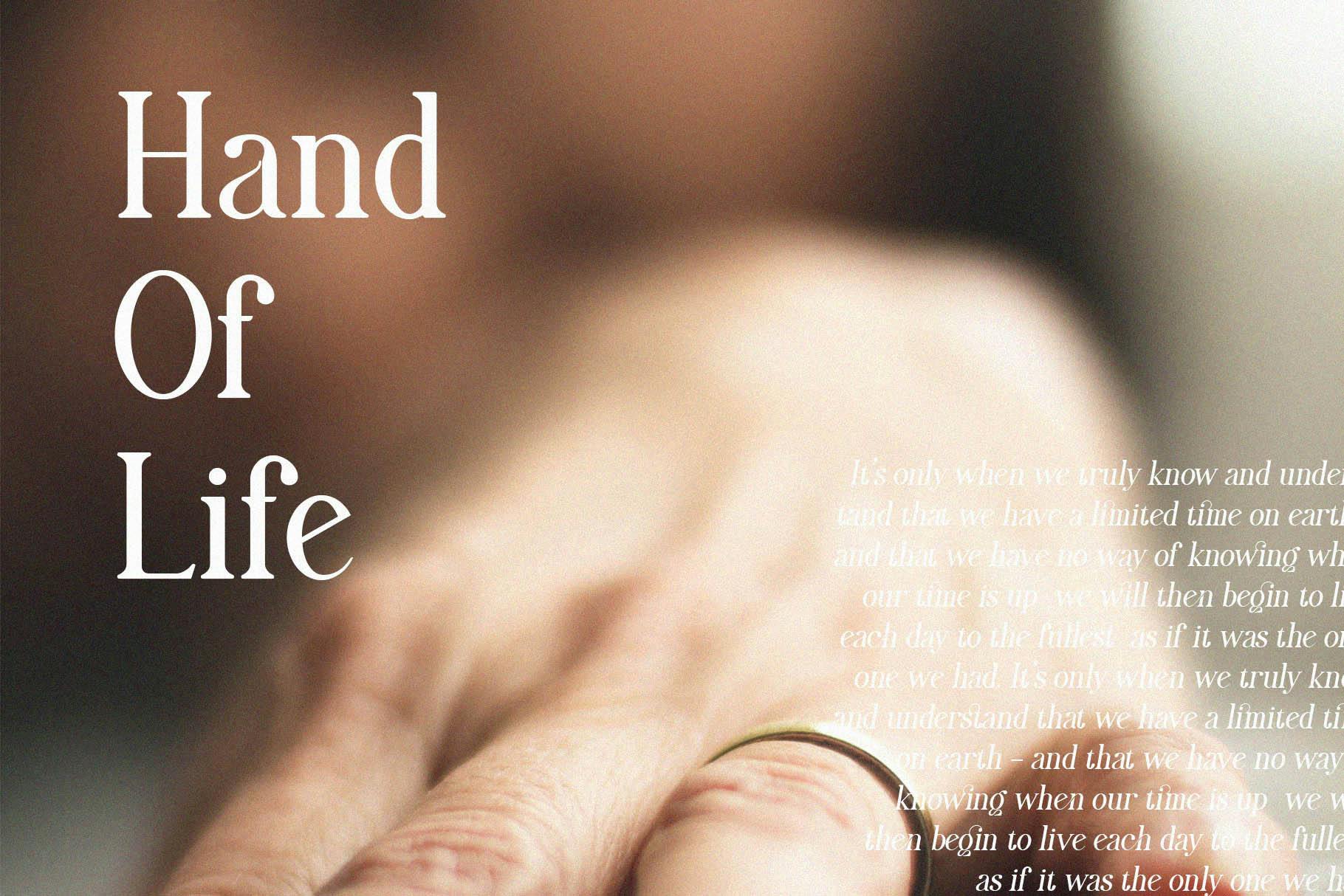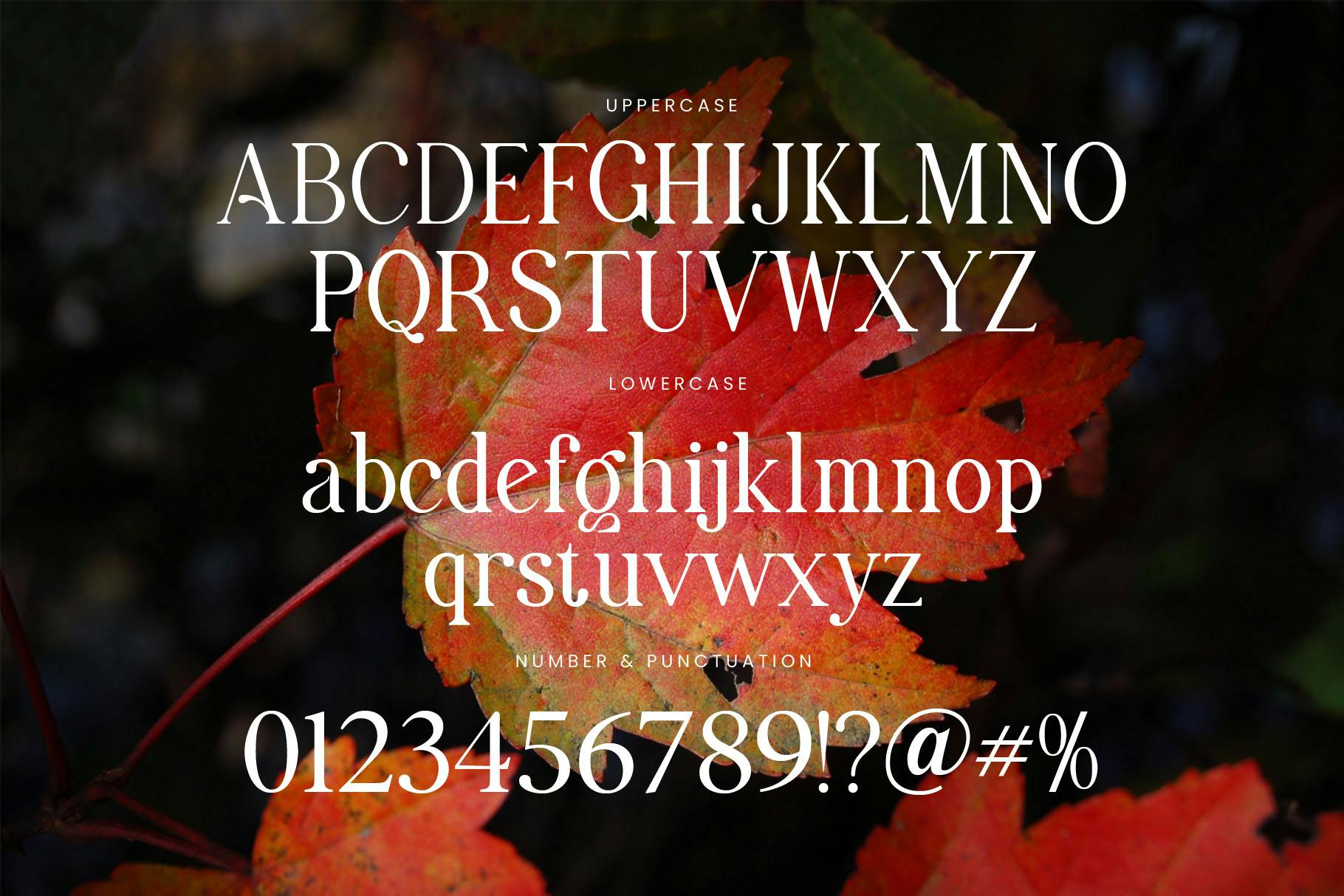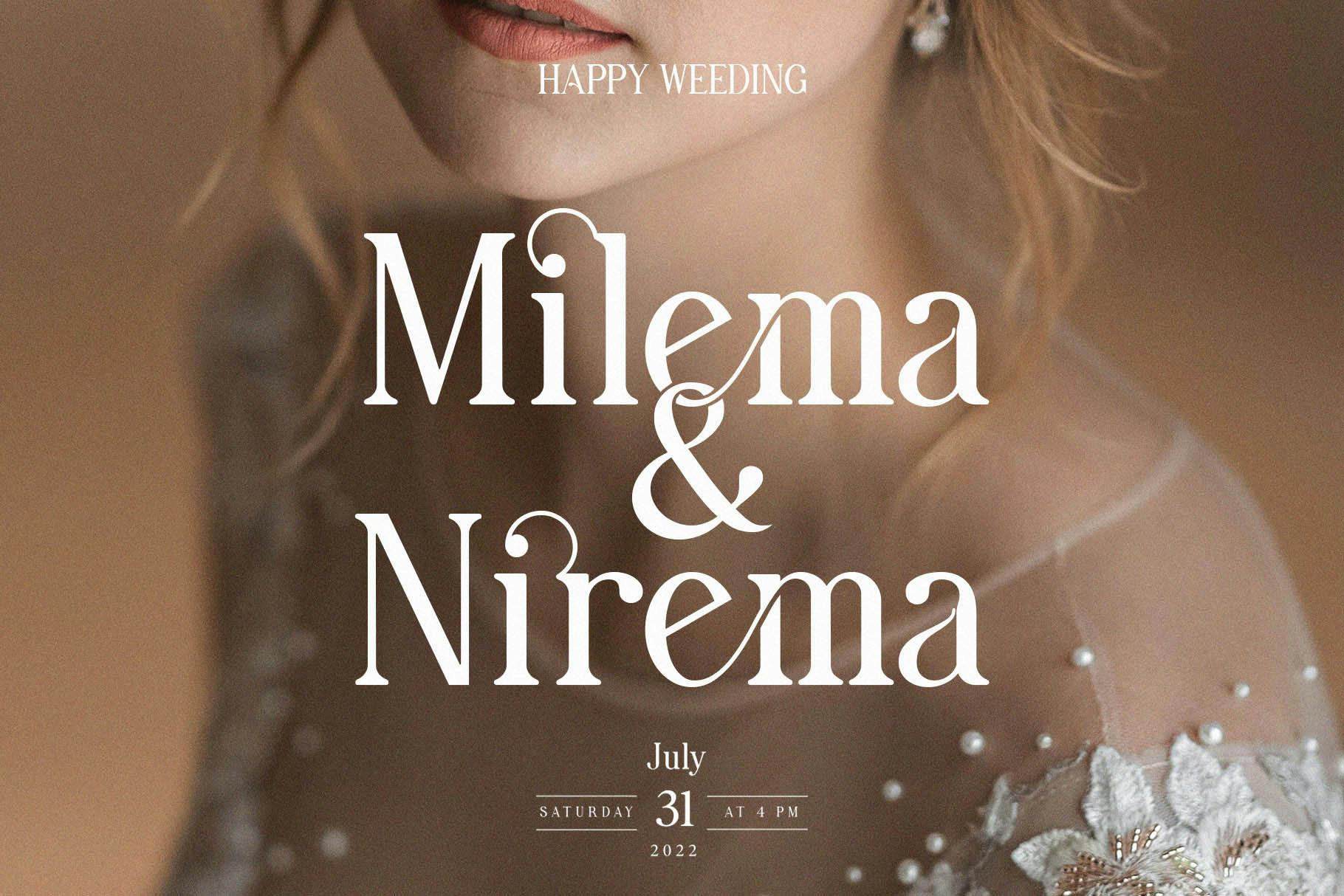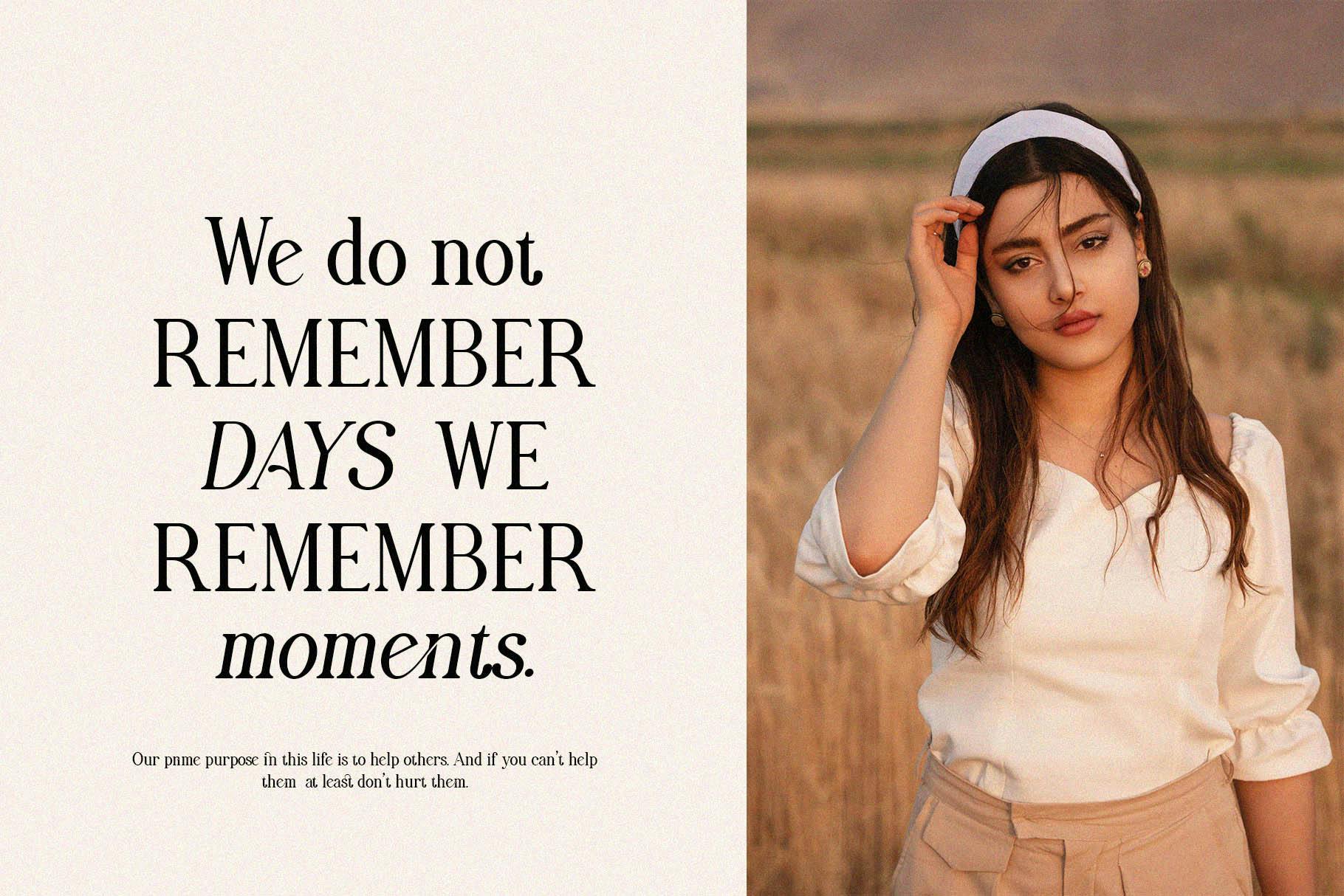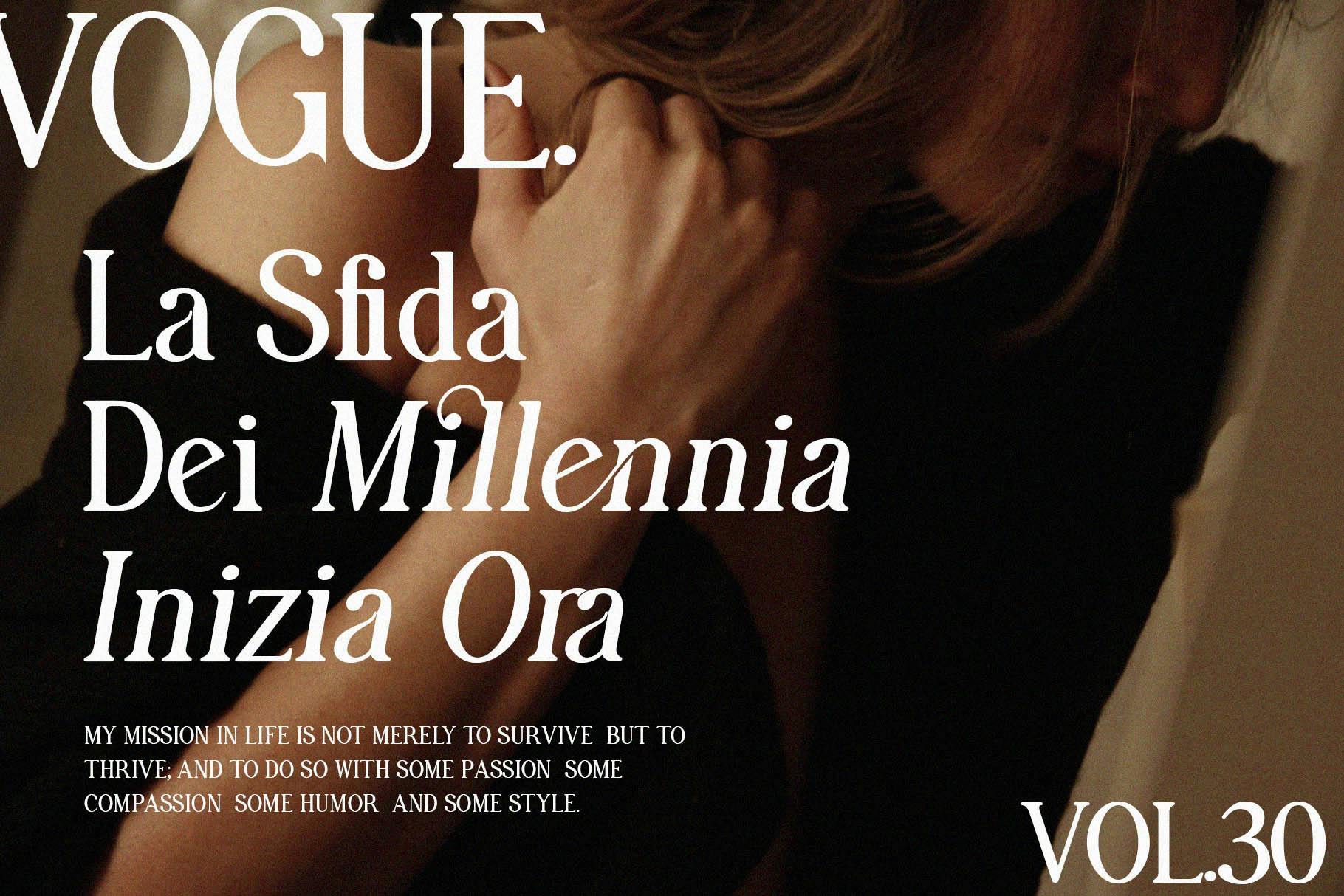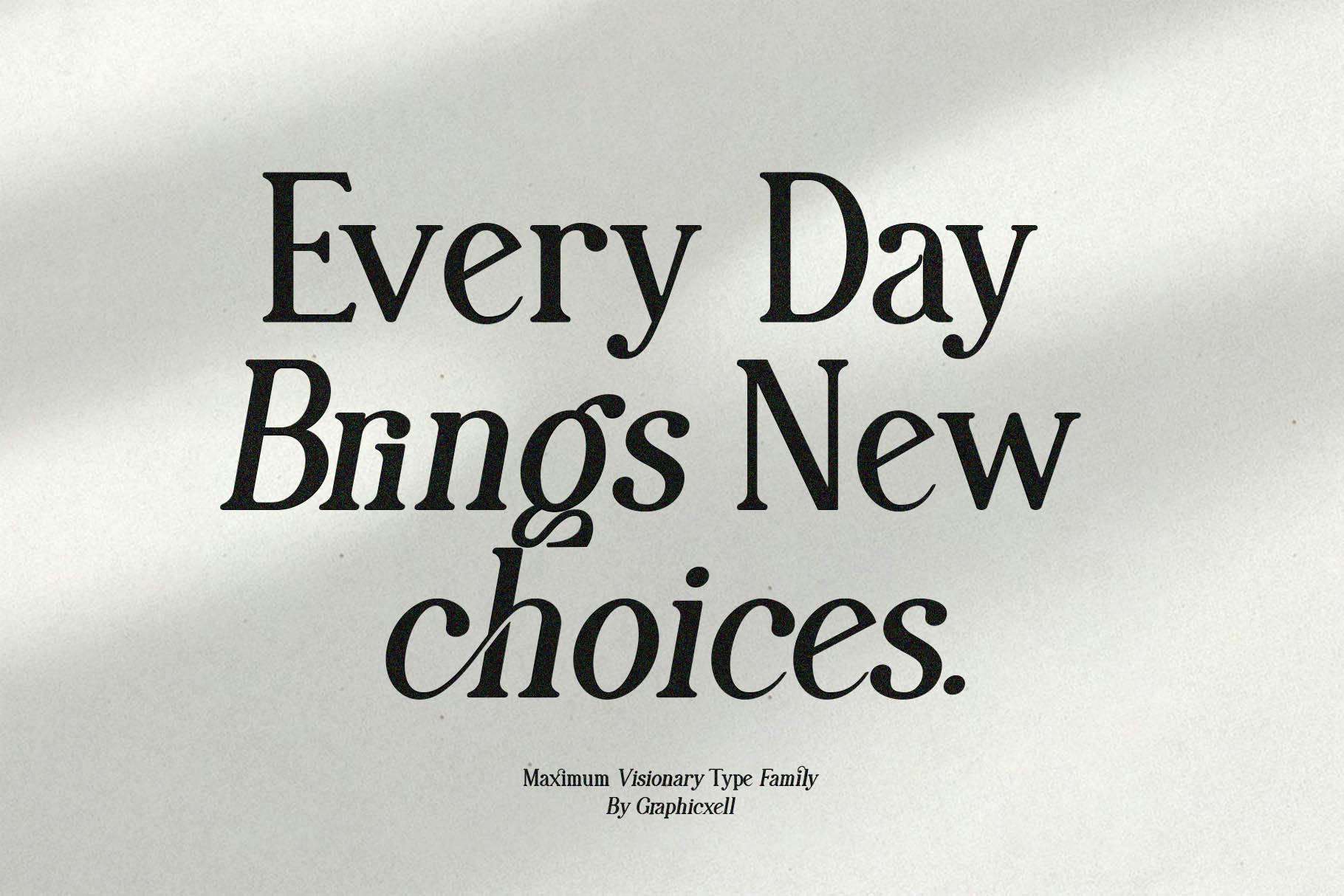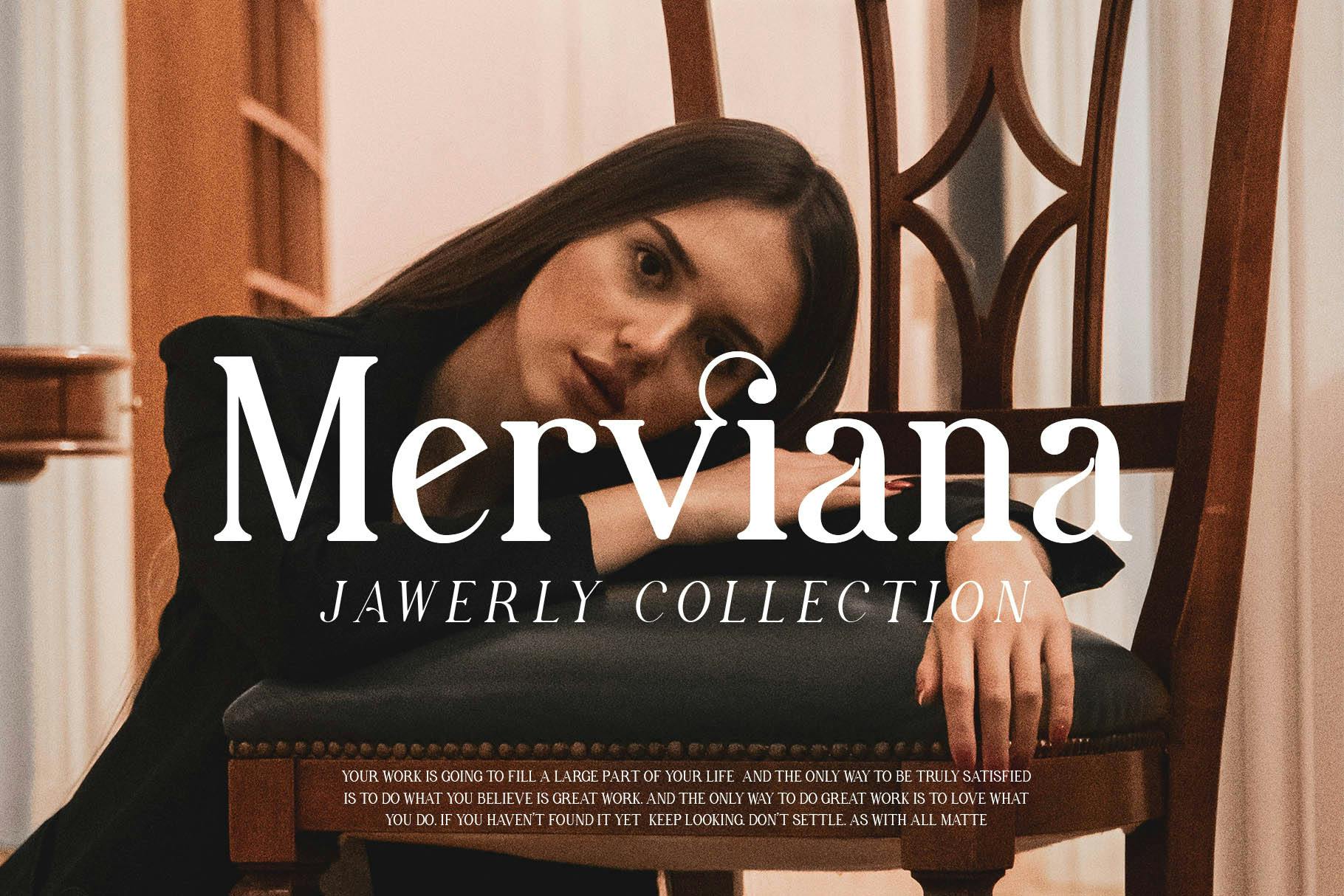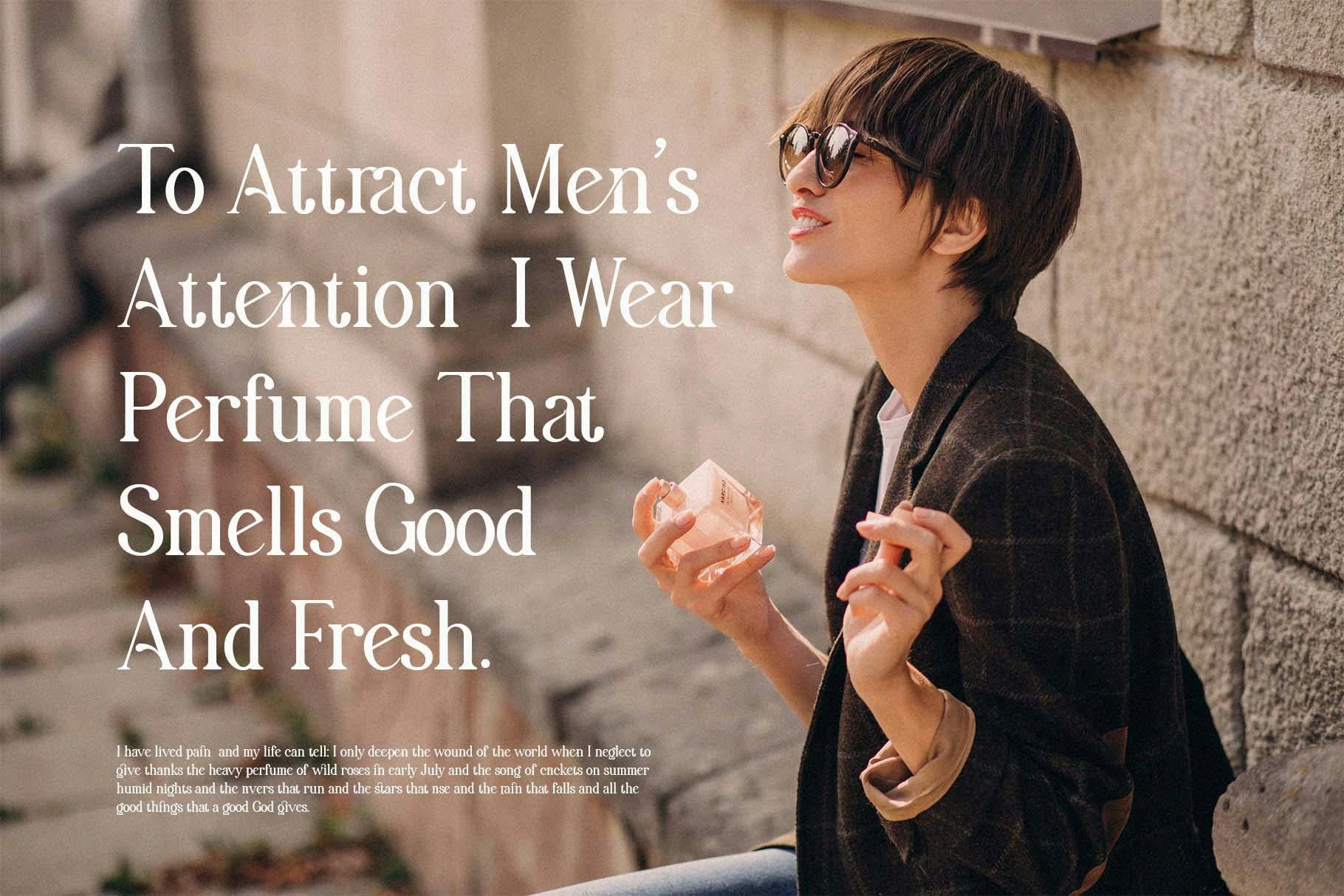
فونت سرس Elegant Serif با نام Maximum Visionary از لوگوهای مینیمالیستی معروف الهام گرفته شده و برای طراحی قالبها، بروشورها، ویدیوها، برندینگ تبلیغاتی، لوگوها، دعوتنامهها، طراحی لایهبندی، هنرهای زیبا و موارد دیگر مناسب است.